William Morris es un artesano multifacético del movimiento Arts and Crafts, sus diseños tipográficos están estampados en todos sus poemas.
William Morris (1834-1896) tiene sus primeros acercamientos al diseño de tipografía y libros debido a su temprana veta poética, ya que trabaja con sus editores en la realización de la impresión de sus poemas y manifiestos políticos, aquí un breve ejemplo de sus tipografías / fonts.
Golden Type
Morris Gothic
Ornament o Chaucer
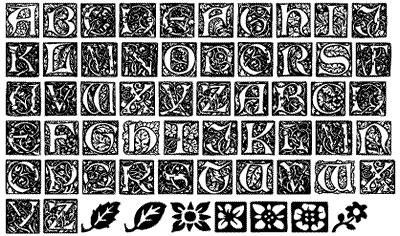
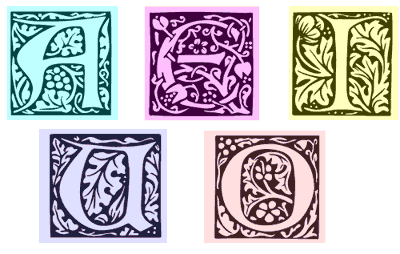
P22 Morris Golden